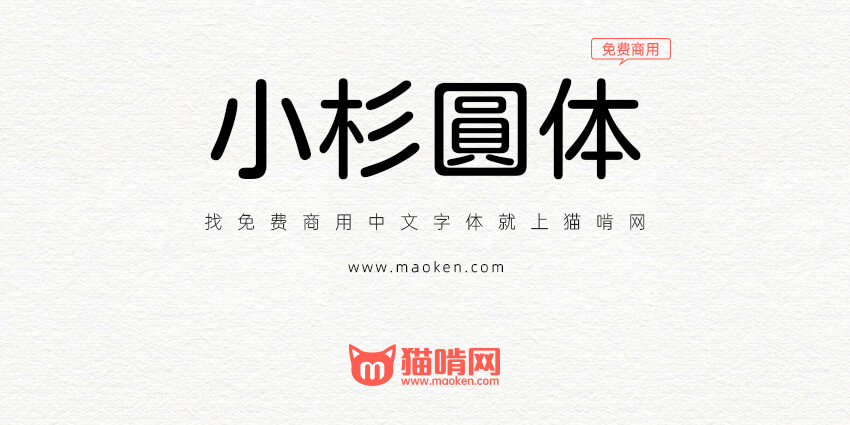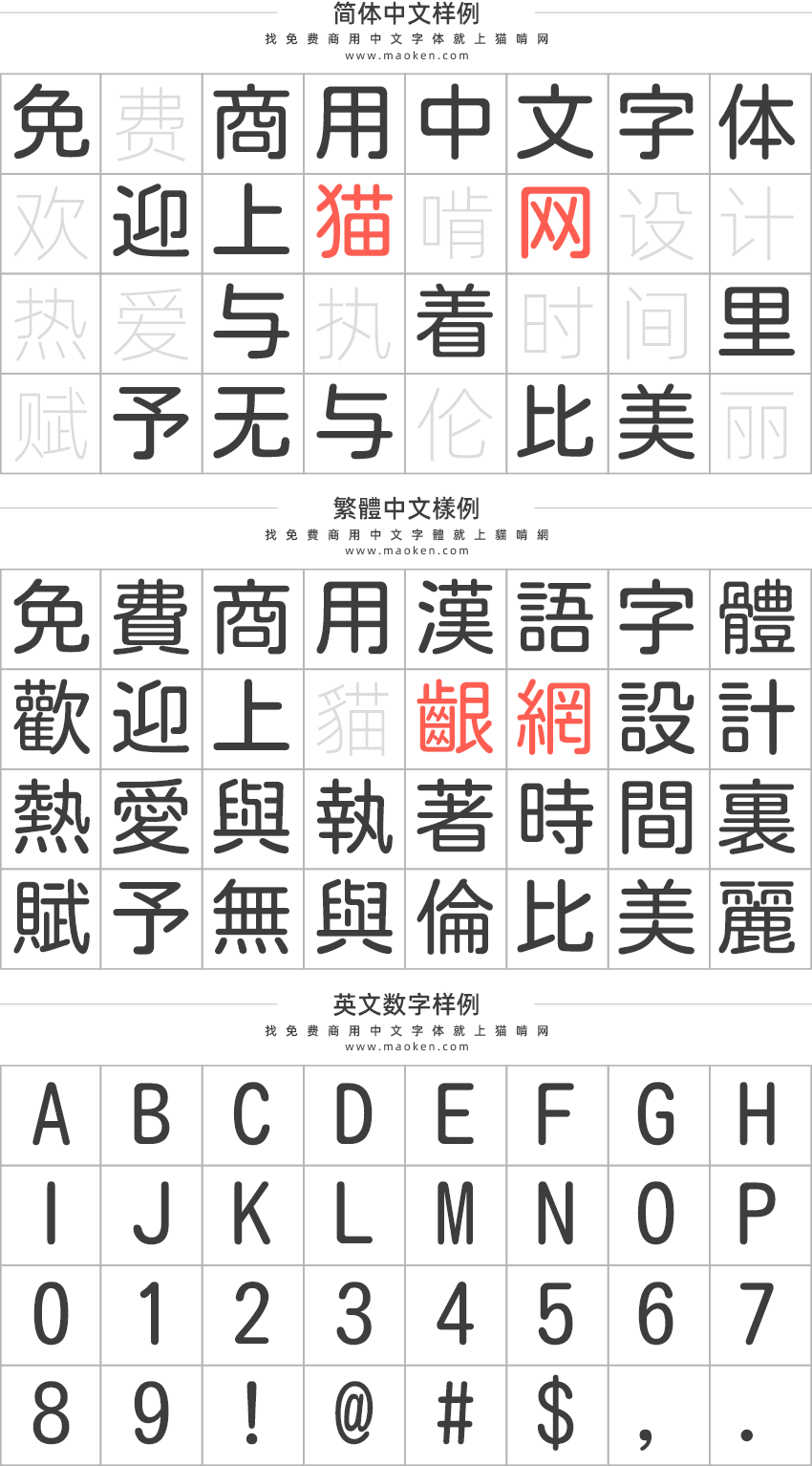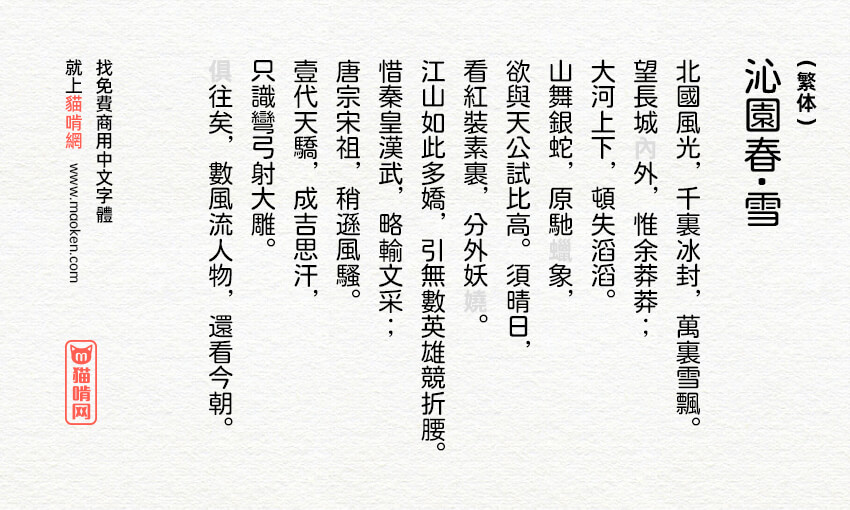
小杉圆体:日本MOTOYA公司出品 免费开源的日系圆体字形
小杉圆体(英文名:Motoya Kosugi Maru),是一款免费开源的日本字体。最初是由MOTOYA公司为Android平台所开发的圆体,现在在Google Font可下载,以JIS第1水准和第2水准进行开发,目前字数共有 7,573 字,已经于许多 Android 手机内建使用,是以Apache 2.0 License进行开源发布。
虽然猫啃网之前已经推荐过 源泉圆体 和 资源圆体 等相关的圆体字形,但是这两款字体都是以圆源黑体进行改造而成的字体,虽然具有圆体的特征,但是缺少了圆体的特色。这款小杉圆体对于中国大陆的小伙伴来说简体字数太少了,使用起来不太友好。
值得一提的是,台湾设计师在2020年3月14日发布一款小杉圆体的改进版本JustFont粉圆字体,而猫啃网基于JustFont粉圆字体发布了补了简体字的猫啃网糖圆体,中国大陆的小伙伴推荐使用猫啃网糖圆体。
感觉这个字体跟华康圆体有点像,尤其是西文
如果我没猜错的话,那个MTLmr3m应该就是它了,不过相比近两年的“粉圆”、“糖圆”,我更喜欢早期有人用“源泉圆体”补齐的版本,感觉这个版本更舒服一些,虽然源泉圆体自身也有不少瑕疵
台湾设计师将在2020年3月14日发布一款小杉圆体的改进版本,猫啃网将会持续关注并第一时间更新,敬请大家期待。
• 粉圆字体就是这个小杉圆体的改进版本~~我剧透一下,简体版本也即将会有的了